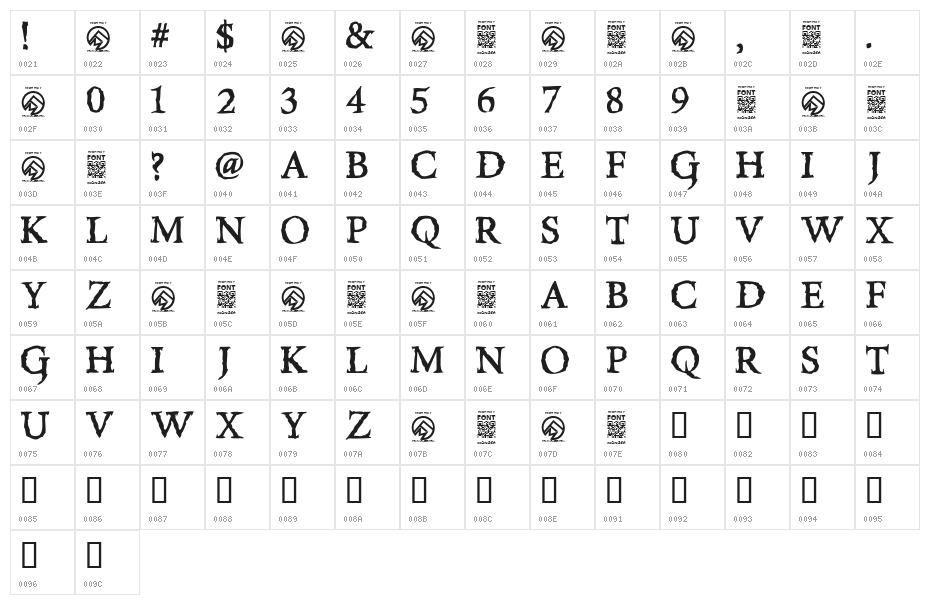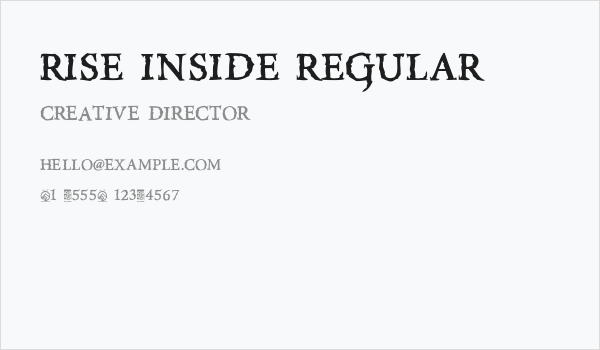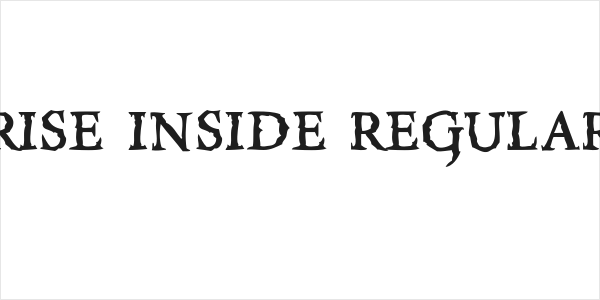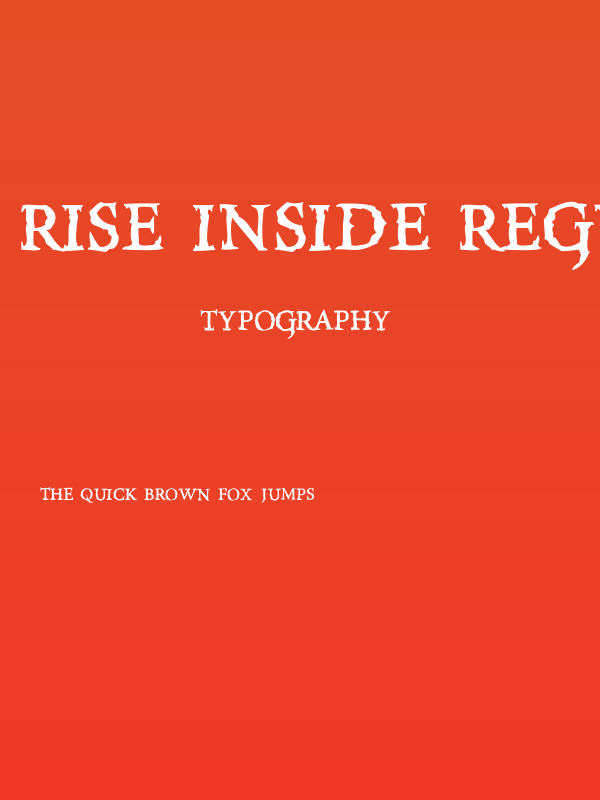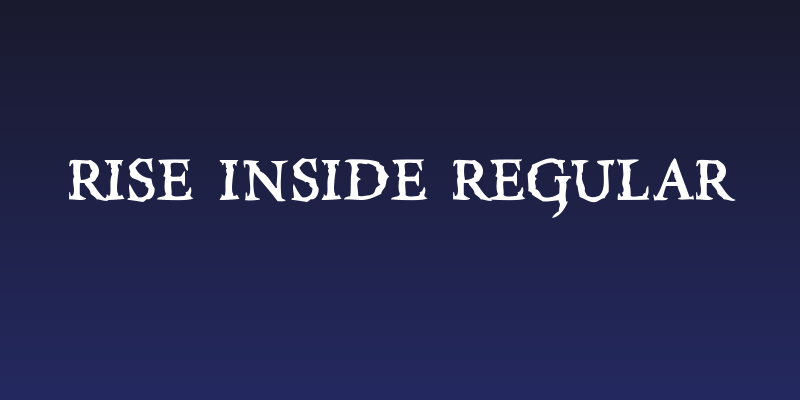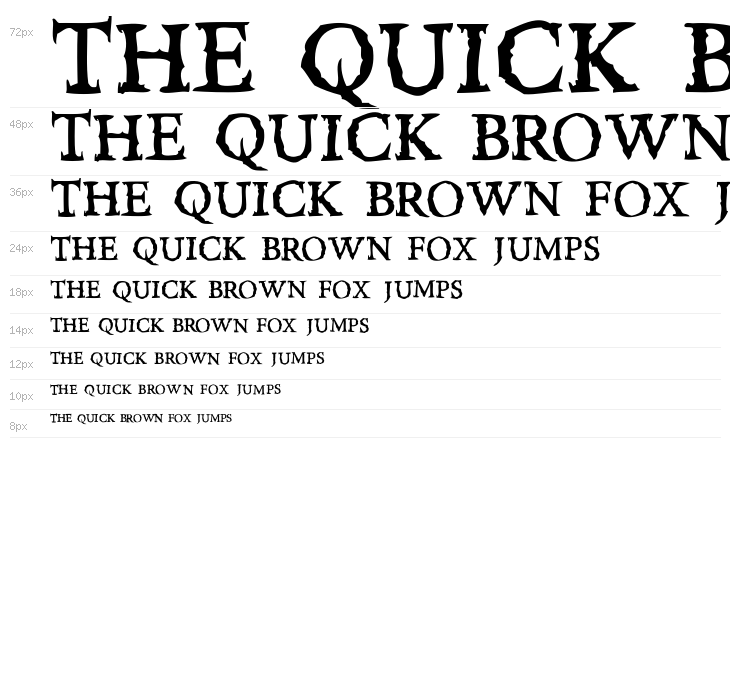
Rise Inside Regular Font
| Progetti proposti | Ideal for posters, album covers, branding for edgy or alternative products, and any design needing a strong, impactful typeface. |